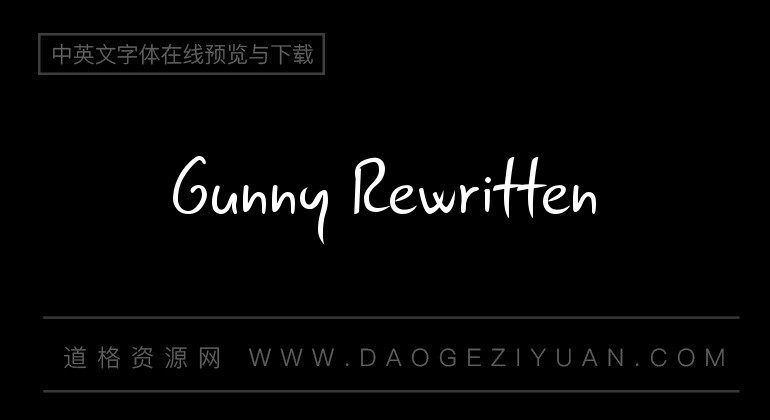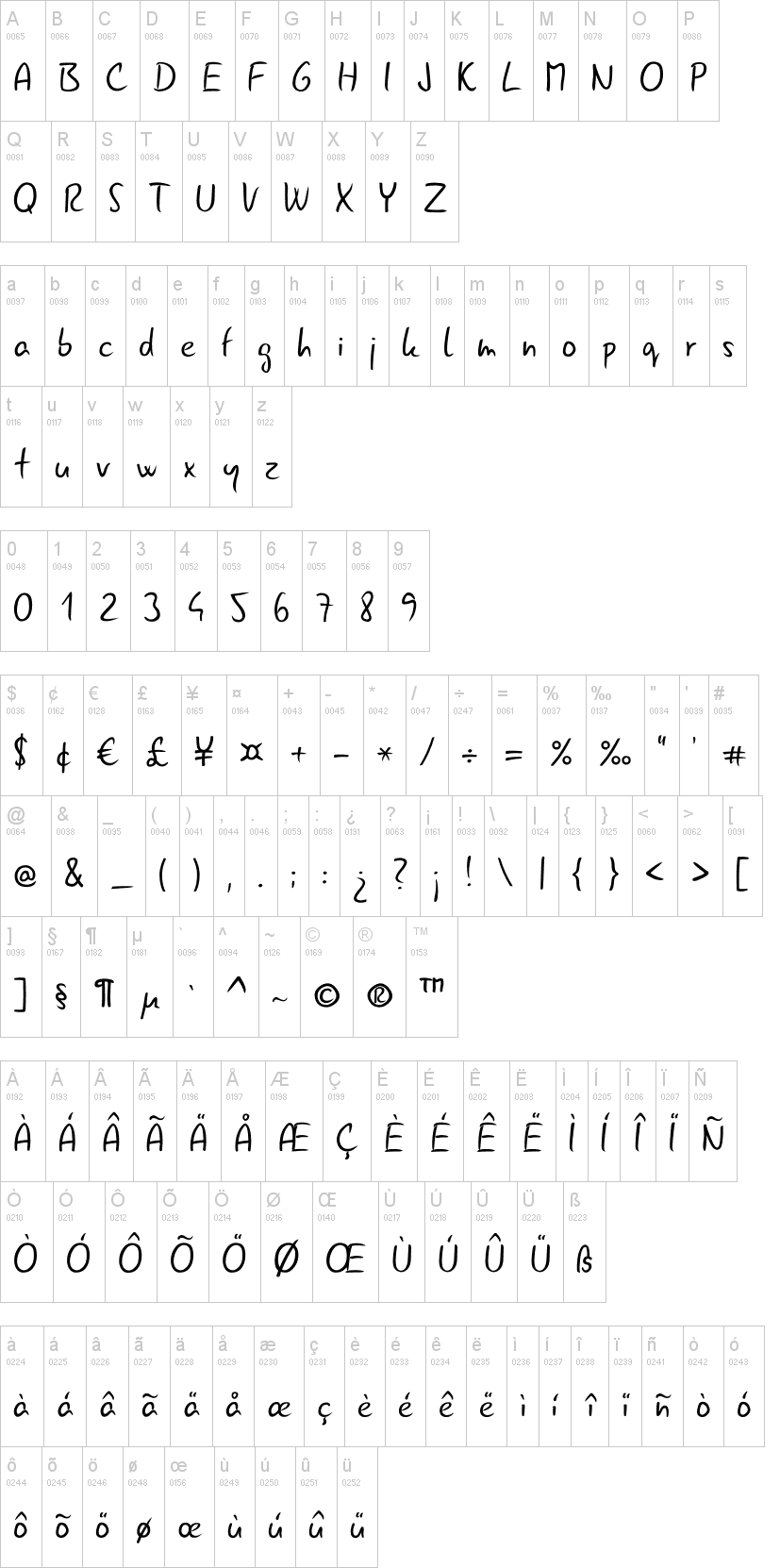
Gunny Rewritten是一款经典游戏字体,它源自于台湾网络游戏《炮兵》,由台湾设计师林瑞珊设计。它采用英文字母和数字的结合,融入了灵动的曲线和节奏,带有一种温暖的复古感。它的字体特征有着粗犷、活泼的视觉效果,搭配上精细的细节,具有独特的设计风格,可以让游戏中的字体更加生动有趣。内容介绍
Gunny Rewritten是一款非常不错的手写艺术字体,具有很好的视觉感,适合于文化类的宣传设计、商业类品牌的广告和产品包装设计以及个性化文字排版等较多场景。